第16回 秋田県立近代美術館で秀英体と会いましょう
秋田県横手市にある秋田県立近代美術館は、1994年に開館した美術館です。代表的な収蔵品に、秋田藩主・佐竹曙山や家臣の小田野直武らの描いた「秋田蘭画」があります。これは、江戸末期に遠近法・陰影法といった西洋の絵画技法を使い描かれた、日本初の洋風絵画として知られます。また、秋田といえば! の日本画家・福田豊四郎、平福百穂など、地元ゆかり作家の作品も数多く収蔵しています。
美術館におじゃましたのは2月、雪深い秋田ですが、ちょうどその日はあたたかく、コートもいらないほどでした。
青空! かまくらの間に見えるのが美術館です。
秋田県立近代美術館には、所蔵品や世界の名作を高精細な画像で鑑賞できる「ハイビジョンギャラリー*1」があります110インチ、60インチ、32インチのディスプレイが設置されており、来館者の方は自由に迫力の大画面でじっくり鑑賞することができます。
110インチのディスプレイが設置されている部屋
こちらは60インチ
今回、秋田県立近代美術館にお邪魔したのは、このハイビジョンギャラリーの表示用書体として、昨年から試作を行なってきたディスプレイ表示用秀英体が採用されたためです。
1994年の開館から運営されてきたハイビジョンギャラリーですが、ちょうどシステムをリニューアルすることになりました。以前から秀英体が搭載されていましたが、タイミングよくディスプレイ表示用の書体に取り組んでいたところでもあり、このたびの採用となりました。
データベースは作品名・作家名で検索します。検索結果は制作者名・タイトル・作品解説と作品画像が表示されます。それ以外にもっと詳しい作者略歴や誰に師事したか、といった情報は、モニターのそばに設置されたプリンターから出力することもできます。この画面表示とプリントアウト用にディスプレイ表示用秀英体が活躍しています。
リニューアル作業中
検索結果はプリンターで出力し、情報を持ち帰れます
検索画面もすべて秀英体
もちろん見出しも
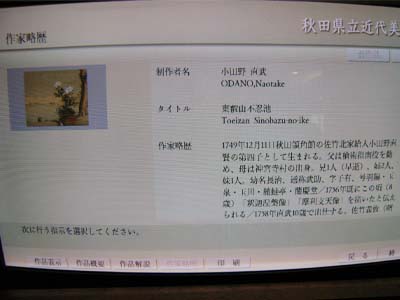
検索結果。写真がうまく撮れませんでしたがこれもすべて秀英体。
ちなみに今回搭載したウェイトは試作した3種類の真中であるM、仮名は秀英4号を合わせています*2。かなりシックです。秋田県立近代美術館の収蔵品にもうまくマッチしているように思います。
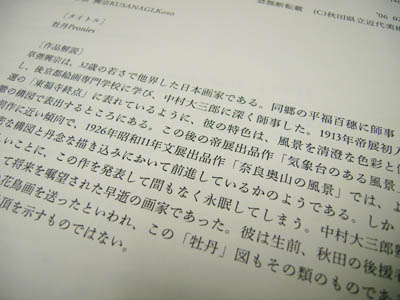
プリントアウトしてももちろんきれいですよ
秋田県立近代美術館のハイビジョンギャラリーは、郷土の作品(秋田県立近代美術館名作撰)・日本の名作(日本美術の至宝)・世界の名作(世界の美術館)という3本立てになっているところが特徴です。今回のシステムリニューアルで検索スピードも格段にアップしたので、今まで以上に楽しめるシステムになりました、とのことです。
ディスプレイに文字を表示することは、印刷とはずいぶん勝手が違います。まず解像度が印刷に比べると圧倒的に低いため、明朝体の特徴である細い横画やしゅっと伸びたハライなどが、可読性を妨げてしまいがちです。また、モニタのしくみや画面解像度、輝度、あるいは表示するシステムの描画エンジンなどによって、文字の表示結果が異なることがわかりました。
ディスプレイで文字がくっきりと表示できること、これがまず第一です。しかしその後には必ず「どう伝えたいか」という表現力が求められるのではないでしょうか。明朝体は日本の文字表現の世界ではスタンダードとして使用されています。デジタルメディアでも「明朝体で」という声をたくさん頂いております。秀英体の持つ表現力をディスプレイでもきちんと発揮させていけるよう、今後とも調査・研究を進めて参ります。
- *2 文字のデザインは今後変更になる場合があります。